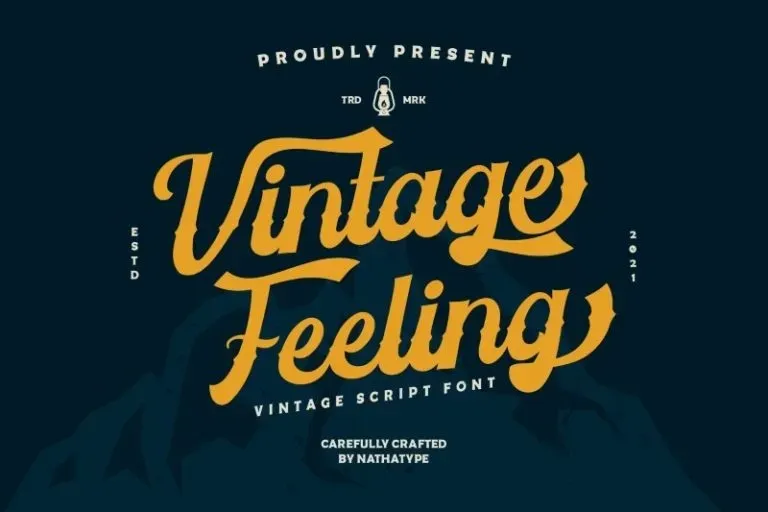
A Vintage Feeling Font é uma combinação deliciosa de retro-tipo dos anos 80 e um estilo tipográfico grosso, criado para projetos que precisam de um toque artístico e sofisticado. Com recursos do tipo aberto que oferecem muitas alternativas e terminações finais, essa fonte facilita a criação de belíssimas escrituras. Além disso, seu estilo artístico a torna uma escolha ótima para diversos projetos, desde logomarcas até cartões promocionais. A Vintage Feeling Font é perfeita para qualquer necessidade gráfica: sua versatilidade faz dela um pacote all-in-one indispensável para qualquer projeto de logo, capa de livro, panfleto, camisetas, marca e anúncio. É uma excelente opção para quem busca adicionar personalidade aos seus trabalhos.